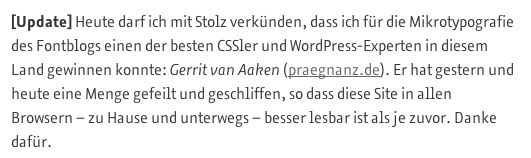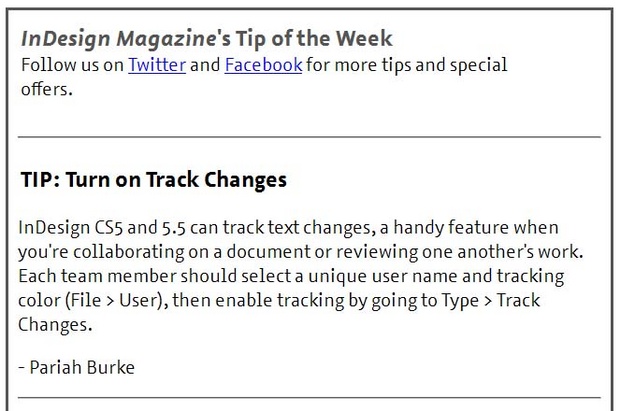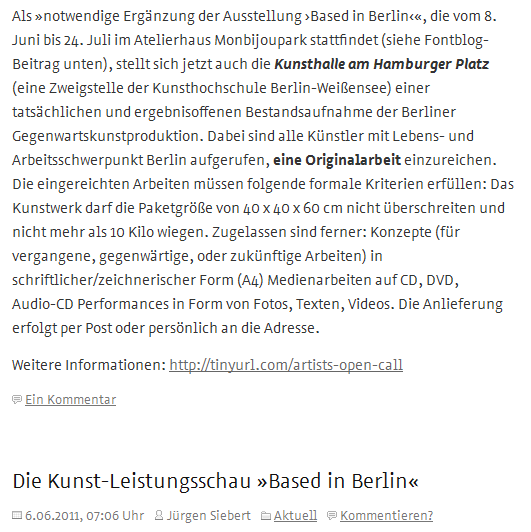
Azuro-Familie als Sonderangebot
Hübsch ist m.E. besonders die Kursive. Allerdings hat sie mich als ausgeprägte Bildschirmschrift innerhalb der letzten zwei Stunden noch nicht so recht überzeugt. Das mag sich aber in den nächsten Tagen auch noch ändern. Bei dem Preis ist es schließlich letztlich auch egal. ;-)
Auf den ersten Blick sehr hübsch, auf den zweiten enttäuscht sie aber. Gerade im direkten Vergleichen auf der von dir verlinkten fontblog-Seite ist die Azuro die am schwierigsten erfassbare und am schlechtesten lesbare Schrift.
Das Illuminat der Azuro sieht fast aus als hätten zwei Versal-i nach einem gemeinen l Platz genommen. Der i-Punkt ist auch viel zu groß geraten. Oder als wären die gemeinen l aus einem Slab-Font eingefügt worden. Verdana und Lucida G finde ich in dem Vergleich als die am besten lesbaren.
Auch das Beispiel der fiktiven E-Mail überzeugt mich überhaupt nicht.
- Die Schrift läuft viel zu eng, um sie schnell lesen zu können
- Das gemeine l mit seinen Serifen stört den Lesefluss in der serifenlosen Schrift
- Das gemeine l ist zu hoch geraten
- Das Q passt nicht zum Rest und hat einen viel zu großen Abstand danach …
In der Schriftgröße des E-Mail-Beispiels ist für mich die Verdana am besten lesbar.
Jepp. Verdana und Lucida kann man in diesem Bereich auch schlicht nicht schlagen. Hat mich auch gewundert, dass Jürgen die Azuro auf diese Weise antreten lässt. Ich würde viel eher darauf abzielen, dass die Azuro auch in kleinen Graden am Bildschirm eine charakterstarke (und damit für Corporate Design taugliche) Schrift ist. (So mancher andere Druckschrift-Klassiker versagt da kläglich)
Aber gerade in kleinen Größen funktioniert sie m.E. am Bildschirm sogar ganz ausgesprochen schlecht. Charakterstark vielleicht, nützt aber ja nichts wenn ich sie nicht ordentlich lesen kann.
Daß sie z.B. hinter Verdana nicht hinterher kommt ist ja auch schon zahlreich in den Fontblog-Kommentaren angemerkt worden. Und so ganz nebenbei und als persönlicher Kommentar: für mich schlägt ja die Frutiger sowohl Verdana als auch insbesondere Lucida am Bildschirm um Längen. Ich habe mein gesamtes System auf die Frutiger umgestellt. :twisted:
Mich wundert diese Aussage im ersten Absatz wirklich sehr:
Azuro ist wahrscheinlich die erste Schriftfamilie, deren Bildschirmverhalten bereits in der Entwurfsphase unter Windows, Mac-OS und Apple iOS unermüdlich getestet wurde, einschließlich Rückwirkung auf den Designprozess.
Ist das die Meinung von Jürgen Siebert oder von Georg Seifert?
Im PDF sieht die Azzuro teilweise recht mau aus, zumindest unruhig, längeres Lesen würde ich mir nicht antun. Und der direkte Vergleich mit den Win-Systemschriften ist ein Witz …
Was sagt ihr zum Zuwachs von Regular nach Bold? Der Unterschied ist schon ganz schön heftig. Jürgen Siebert schreibt dazu im Fontblog:
Der Unterschied zwischen Regular und Bold ist stärker ausgeprägt als bei manch anderen Bildschirmschriften (und stärker als bei Druckschriften sowieso), damit sich fett gesetzte Wörter oder Textpassagen am Bildschirm ausreichend stark gegenüber dem Grundtext abheben, ganz egal wie stark dir Konturenglättung (-vergrauung) bei einem Rechner eingestellt ist.
Da man im Fontblog nicht den vollständigen Zeichenvorrat sehen kann, habe ich mal eine pdf-Datei mit allen Glyphen der drei Gewichte gemacht. Einfach auf folgendes Bild klicken.
Was sagt ihr zum Zuwachs von Regular nach Bold?
Mir persönlich ist die Regular am Bildschirm einfach zu dünn. Die Bold finde ich ja nach wie vor gut ... :party:
Da schneidet bei mir persönlich ja direkt aus Acrobat (wofür die Azuro ja angeblich auch gut sein soll) die Graublau Sans eindeutig am besten ab. Geht das nur mir so? Bei der Azuro erscheint mir am Bildschirm die Vertikale so extrem; sie »führt« mich so gar nicht in der Leserichtung. Im Druck stört mich das viel weniger. Im Gegensatz zur derzeitigen Vermarktung kann ich mir sogar vorstellen daß ich sie gerne für fette Überschriften insbesondere im Druck einsetzen werde.
Ich habe gerade gelesen, dass der Fontblog ab jetzt in der Azuro schreibt. Wer sich also mal ein Bild von der Qualität ihrer Bildschirmlesbarkeit machen möchte …
Immer noch nicht schnell genug lesbar und viel zu unruhig.